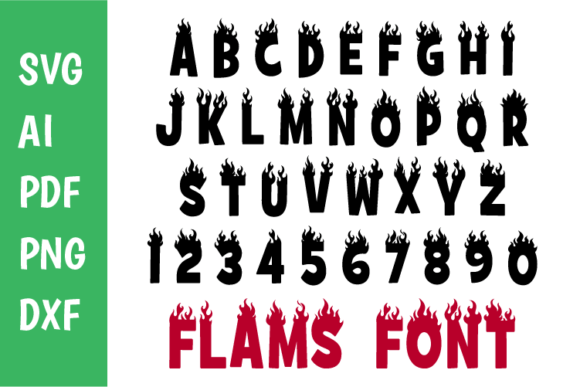
Flame Font Font for Cricut Svg
適切なデザイン要素を見つけるのは難しい場合がありますが、Flame Font Font for Cricut Svgは作品を即座に引き立てる優れたコレクションを提供します。
POD(オンデマンド印刷)製品、結婚式の招待状、またはソーシャルメディアのグラフィックを作成している場合でも、Flame Font Font for Cricut Svgは理想的です。